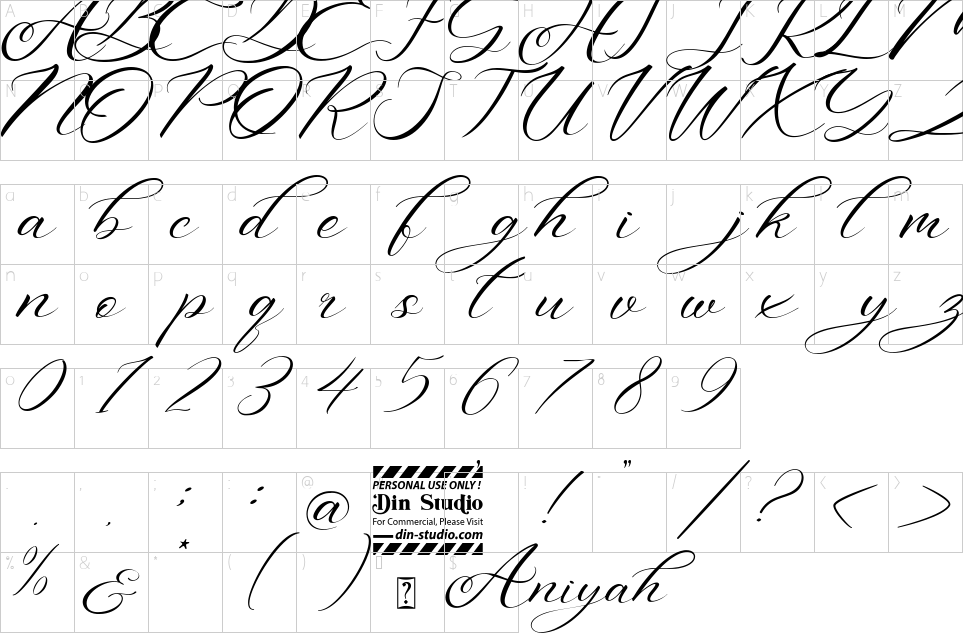
Aniyah é uma fonte gráfica criada pelo designer Donis Miftahudin, disponível para download tanto para sistemas Windows quanto Mac. Esta elegante fonte foi projetada para oferecer uma experiência visual agradável e única em sua aplicação. Com uma paleta de cores moderna e linhas finas, ela se destaca como uma opção versátil para design gráfico, preservando seu carácter tanto em textos leves quanto em elementos gráficos mais dramáticos. Com seu design limpo e sofisticado, Aniyah é perfeita para usar em qualquer projeto que busque uma paixão gráfica moderna e sofisticada. Para os amantes de design gráfico, Aniyah representa uma fonte gratuita e de alta qualidade.